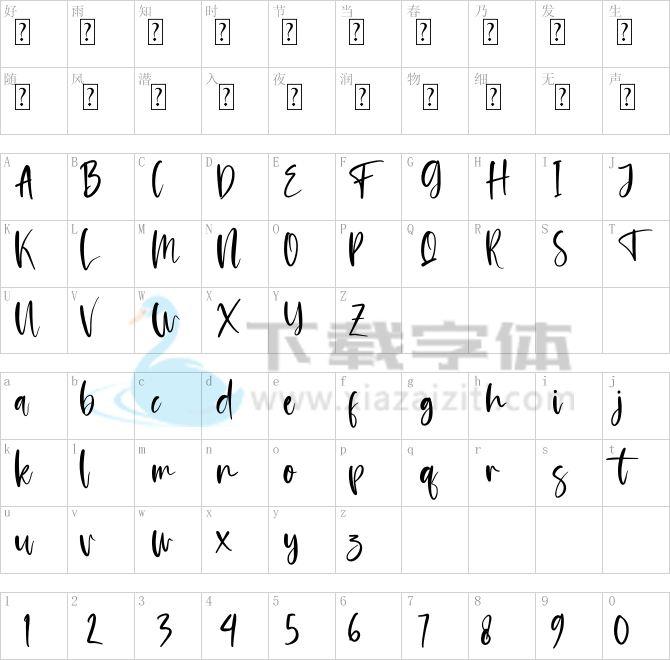
Amsterdam Morning.ttf字体下载,这款字体结构工整、笔画清晰,兼顾美观与易读性,适用于标题、正文、海报、包装、LOGO 等多种场景。字形优雅稳定,风格百搭耐看,适配日常排版与创意设计,让文字呈现更舒适、更具质感。Amsterdam Morning.ttf字体下载一笔一画,皆是细节,以均衡的比例、流畅的线条打造舒适视觉体验,字形端正大气,风格简约现代。无论是商业设计、品牌宣传还是日常排版,都能轻松驾驭,让文字更有格调与力量。Amsterdam Morning.ttf字体下载字体下载。